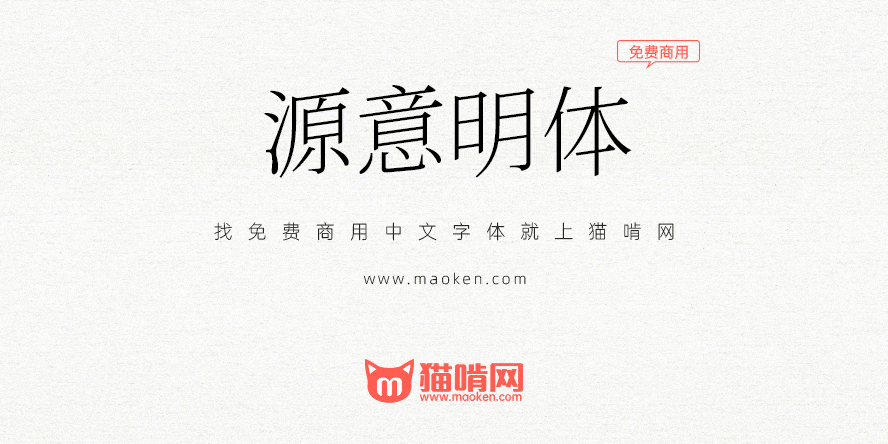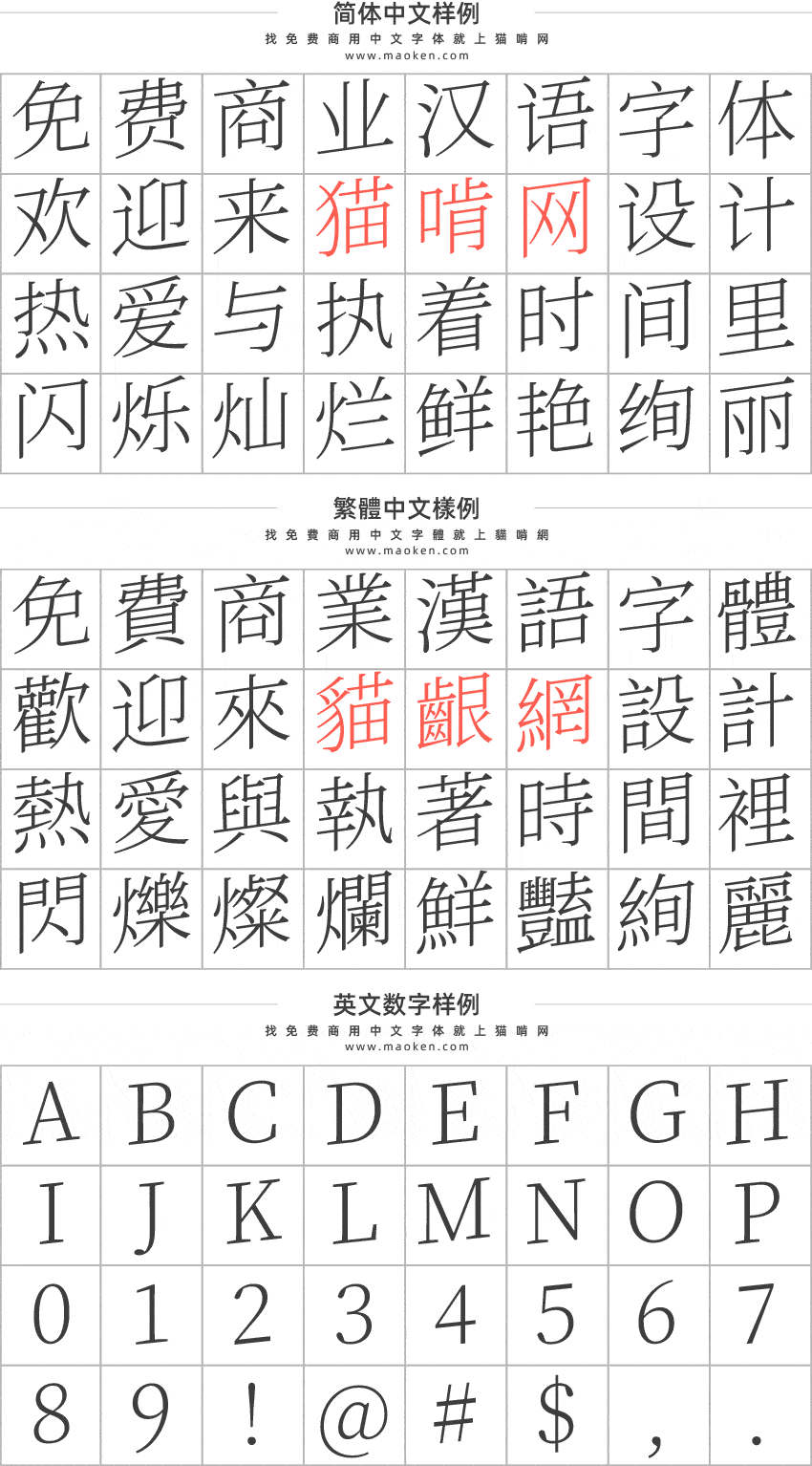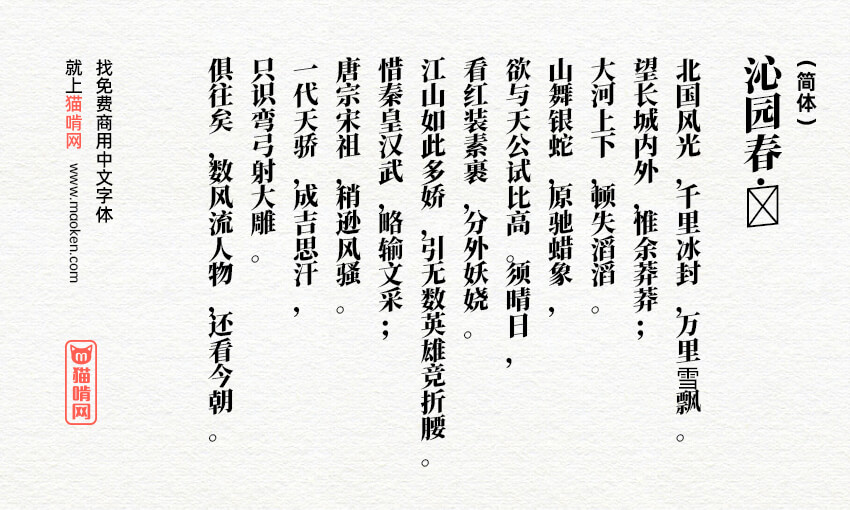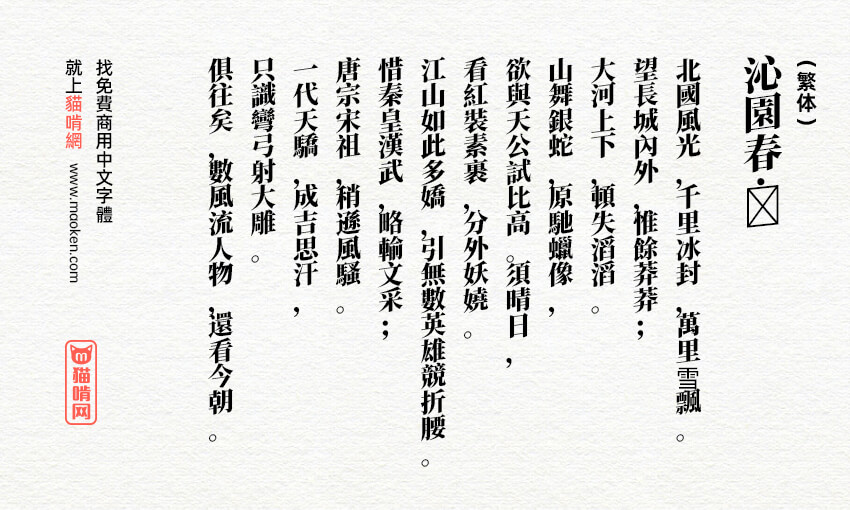
| 字体作者:綿雲飴里 (中国大陆) | 字体字重:可变 |
源意明体是字重可变字体。不支持可变字体的旧系统\软件只能显示为超细,是正常现象——我用的也是旧系统。也会制作不可变的字重方便(我自己)使用。
虽然是用可变思源宋大陆款〔Source Han Serif CN VF〕改的,但许多符号是有意缺失:比如“☂☎⚽”这些不存在斜体概念的,和没有衬线体\宋体形式的。遇到缺字情况可用原版可变思源宋补充,但意义不大——这些字符在原版里本来就不是衬线风格的。
我暂时删除了所有注音符号,直到思源更新
这次不全靠机械倾斜了,参考了仿宋和颜真卿写法。我调整了百来个汉字和英文f等等,还修了思源宋自身的错误,如adobe-fonts/source-han-serif#131 ,添加思源宋没有的𠚤(U+206A4)字。
★如图,还发明了衬线体的意大利体☆
倾斜会导致字义改变(尤其箭头)的、“ℊℓ”这些已经是斜体形式的则不改。
楷体风格的假名有意没改,毕竟宋体的意大利体形式经常用楷体表现。
此外包含思源宋大陆款的一切错误:Missing Glyphs in CN Subset like 霜, 雪, 需, etc. · Issue #106 · adobe-fonts/source-han-serif,连箭头的“箭”字都没有。
推荐同时安装这2个字体,这样对SrcMing(正体)使用 I 倾斜 按钮时,SrcMing不会横向倾斜而是直接调用 SrcMingItal2 (写体)。试试看~
- 未来计划:把片假名改成宋体风格。
ag等应该也要改成意大利体,不过思源宋自带的ɑɡ不太好看……
- 调整了〢〣以与二三搭配;改乄(⿻㇢㇔)为宋体;继续调整了若干写体汉字。添加苏州码子相关的calt特性:〡〡〢〡〣〡〢〢〢〣〣〣〡〢〣〢〡〣连写会自动切换为〡一〢一〣一〢二〢三〣三〡二〣二〡三。
- 临时添加2个特粗(Extra Bold,Xb2)字重的(普通,非可变)字体方便使用。